아랍어 폰트 디자이너_나딘 차하인
“From the Inside, From the Heart”
나딘 차하인(Nadine Chahine)은 아랍어 폰트(Arabic fonts)를 전문으로 디자인하는 서체 디자이너이다. 서체 디자인으로 상을 받기도 한 그는 2005년부터 라이노타입(Linotype)에서 디자인 업무와 판매 마케팅 업무를 병행해 오고 있다. 라이노타입의 아랍어 서체 디자인 프로그램이 탄력을 받게 되면서 그녀는 폰트 개발 업무에 집중하기 시작했다. 레바논 태생의 나딘 차하인은 베이루트 아메리칸 대학교(American University of Beirut)에서 그래픽 디자인을 전공하면서 서체 디자인 분야에서의 경력을 쌓았으며, 일찍부터 아랍어 폰트 디자인의 가능성에 관심을 갖게 되어 레딩 대학(University of Reading)의 서체 디자인 석사과정에서 보다 깊이 있는 공부를 시작했다. 그는 일상적인 업무 속에서 목표를 세워두고 디자인에 대한 시야의 확장을 실현해 나가고 있다. 이 목표를 위해 그는 네덜란드의 레이던 대학교(Leiden University)에서 박사과정을 수학하면서 아랍어 문자의 가독성에 대해 집중적으로 연구하고 있다.
Catherine Dixon (이하 CD):
먼저 고백할게요. 저는 아랍어 글자 형태는 물론 서체로 표현된 형태에 대해서도 제한된 지식 밖에 갖고 있지 않습니다. 제가 이해하고 있는 바에 따르면, 잠재적인 디자인의 출발점으로 사용할 수 있는 필기 문자(서예체)의 범위가 있는 것 같은데요. 아랍어 서체 디자이너로서 작업하고 있는 필기 문자의 범위에 대한 전반적인 개요를 말해줄 수 있을까요? 그리고 그 중에서 특별하게 끌리는 필기 문자가 있다면 무엇인지, 그 이유는 무엇인지 궁금합니다.
Nadine Chahine (이하 NC):
아랍어 캘리그라피 스타일은 각진 스타일과 둥근 스타일, 크게 두 가지로 구별됩니다. 필기도구나 의도하는 기능 같은 것들과 관련이 있는데요. 이렇게 나뉘어진 이유는 복잡하죠. 각진 스타일(The squarish styles)은 보통’쿠피(Kufi)’라고 부르지만 정확한 용어는 아니에요. 둥근 스타일을 일컫는 말은 많이 있지만, 보통 참고 문헌에서’나스크(Naskh)’라는 용어를 가장 많이 사용해요. 각진 스타일은 그 이름이 암시하듯이 굉장히 딱딱하게 각 져 있죠. 명확한 수직선과 수평선을 갖고 있고, 전반적인 외관이 기하학적이며 베이스라인에 많이 붙어있어요. 이 스타일의 서체는 원래 초기 필사본의 본문에 사용되었지만, 기념비에 제목용으로 크게 쓰이는데 적합하도록 진화했습니다.
둥근 스타일(The rounded styles)은 구조적으로는 유기적이고, 형태적으로는 복잡하며, 운동감이 느껴지는 흐름을 보여줍니다. 그리고 사람들은 이 스타일이 마치 베이스라인을 따라 우아하게 흐르는 것처럼 보인다고 느끼죠. 이 스타일은’Thuluth’*처럼 큰 사이즈로도 개발되었고, Naskh처럼 본문용 사이즈로도 개발되었어요. Naskh는 8세기가 넘도록 필사본에서 ‘사실상’ 본문용 서체로 사용되었죠.
매우 폭넓은 범위에서 말하자면, 오늘날 아랍어 서체는 Naskh와 Kufi 이 두 가지 스타일에 기초한다고 보면 됩니다. 캘리그라피 형태에서 타이포그래피 형태로 이행하면서 Naskh 서체는 캘리그라피 전통에서 찾을 수 있는 유연함과 우아함을 잃어버리는 슬픈 상황에 처하기도 했죠.
* Thuluth: 아랍어 서예체 중 하나로 사우디 국기의 초록 바탕에 사용되기도 했다.
전통적인 Naskh(둥근 스타일)로 작성된 코란(Quran) 필사본의 상세 페이지
제가 처음 아랍어 글자 형태에 관심을 갖게 된 계기는 베이루트 아메리칸 대학교에서 아랍어 타이포그래피 강좌를 들으면서부터였어요. 그 때 저는 캘리그라피 거장이자 예술 비평가인 사미르 세이예그(Samir Sayegh)로부터 수학했죠. 그의 작품은 대부분 Kufi 스타일로 만들어졌어요. 오스만 제국 시대 이후에 거의 발전이 없었던 아랍어 캘리그라피에 새로운 숨을 불어넣고 있다는 평가를 받고 있는 분입니다.
모더니티를 향한 추진력과 영감을 주는 그의 재능은 많은 학생들의 관심을 사로잡았어요. 이와 같은 수업 과정은 당시 다른 대학에서는 전혀 찾아볼 수 없었습니다. 그때 저는 불이 번뜩이는 것과 같은 그의 비전을 볼 수 있었죠. 그는 오늘날 아랍어 서체 디자인 분야에서 흥미로운 발전을 이끌어낸 인물 중 한 사람입니다.
CD:
아랍 문자와 특정 종류의 텍스트 사이에서 보이는 연관성은 굉장히 흥미로운데요. 라틴 활자 인쇄의 초기 시절과 별반 다르지 않아 보입니다. 특정 필기체가 존재하고 그것이 활자로 만들어졌을 때 특정 맥락과 강력하게 연관되죠. 즉, 특정 언어와 글자 형태 사이의 연관성은 강력합니다. 라틴 문자에서 이런 초기의 연관성은 사라진 지 오래되었는데요. 아랍어 서체 디자인은 여러 가지 면에서 여전히 실용화 초기 단계입니다. 아랍어 필기체를 타이포그래피적으로 해석하는 데 있어서 미래에 어떤 기회가 있을까요?
NC:
아랍어 캘리그래피의 다양한 스타일은 개발 대상이나 유래한 지역 때문에 구체적인 암시를 내포한 경우가 많아요. 예를 들면,’Diwani’는 오스만 제국 초기에 특권층을 대상으로 공식적인 발표와 황실의 칙령에 사용하기 위해 개발되었고,’Maghribi’는 북아프리카의 모로코 지방에서 개발되어 문자 그대로 모로코어로 번역됩니다.
오늘날 아랍어 타이포그래피 분야에서 보여주는 주된 차별점은 헤드라인과 본문 사이의 기능적인 가능성입니다. 각진 Kufi는 헤드라인에 적합하고, 둥근 Naskh는 본문에 적합하죠. 이 두 극단 사이에는 아주 폭넓은 디자인의 가능성이 있고, 저는 디자인할 때 이 부분에 대부분의 시간과 공을 들이고 있습니다.
헤드라인과 본문 각각에는 다른 쪽을 더 좋게 하고 기능을 향상시킬 수 있는 가능성이 있는 특질들이 있어요. 만약 Kufi의 안정성과 규칙의 일부를 Naskh에 적용하면, Naskh 서체는 헤드라인에서 좋아 보일 수 있습니다. 그리고 Naskh의 유동성과 부드러움을 일부 Kufi에 적용하면, Kufi 서체가 본래의 안정성과 견고함을 유지하면서 짧은 본문에서 잘 기능할 수 있는 것이죠.
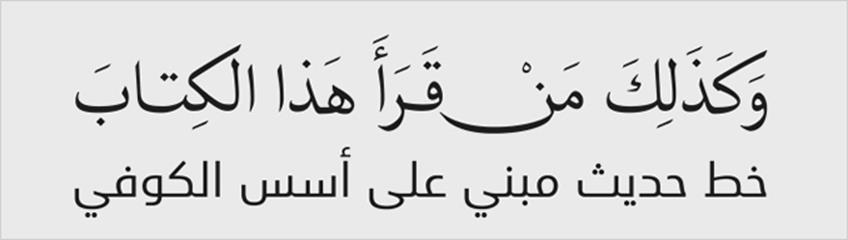
서로 다른 캘리그라피 스타일 예시
Afandem: 전형적인 Naskh 캘리그라피에서 영향을 받은 역동적인 서체
Universe Next Arabic: Kufi 구조에 기반을 둔 현대적인 아랍어 서체 디자인을 구현했다.
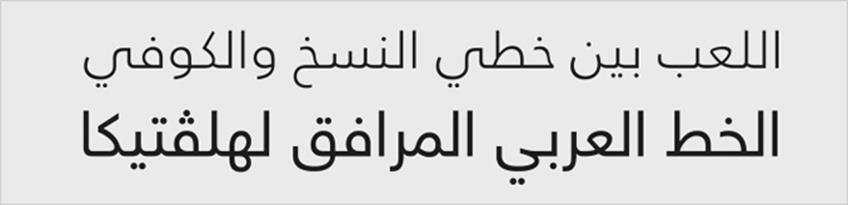
혼합형 디자인 예시. Frutiger Arabic과 Neue Helvetica Arabic
이렇게 작업하는 동안에도, 가장 중요하게 생각하는 부분은 원래의 캘리그라피 형태로 돌아가서 그 형태가 완성된 방식을 이해하고, 그 특징을 최상으로 해석해내는 방법을 찾는 것입니다.
CD:
아랍어와 라틴 문자의 동반 서체 관계는 명백하게 당신이 디자인한 많은 서체들의 핵심이라고 할 수 있습니다. 서로 다른 문자를 동시에 다루며 디자인할 때 고려하는 전략에 대해 조금 더 설명해주실 수 있을까요?
NC:
서로 다른 문자를 함께 디자인할 때 첫 번째 고려하는 사항은 각 문자가 본래 가지고 있는 고유의 시각적 미와 구조를 최대한 살리는 것입니다. 이 부분은 넘어서지 말아야 할 한계선 같은 것이죠. 그 다음 고려사항은 어떻게 두 활자체가 서로 연관되어 있는가 하는 것입니다. 그 둘이 같은 속도로 걷고 있는지, 둘이 같은 톤의 목소리를 내고 있는지, 둘이 같은 방식으로 작동하고 있는지, 그리고 그 둘이 정말로 한 가족의 일부인지. 이러한 사항들을 다루는 건 라틴 문자와 아랍어를 동시에 작업할 때 더 수월합니다. 이것이 바로 Koufiya가 서로 어울리는 동반 서체가 된 방법입니다.
저는 라틴 문자와 아랍어를 교차하며 변화를 만들어냈고, 두 문자가 한쪽에 맞춰 변형되지 않으면서 둘이 함께 목소리를 잘 내는 것처럼 보이도록 노력했습니다. 동반 서체를 디자인할 때는 각 문자가 서로 다른 에너지(dynamics)를 갖고 있다는 사실을 받아들여야 해요. 그리고 이러한 각 문자의 고유성은 반드시 존중되어 디자인에서 잘 설명되어야 합니다. 이중언어로 디자인할 때 보통 아랍어가 라틴 문자에 비해 약해 보이거나 덜 정제되어 보이는 경우가 있는데, 저는 이 상황이 달갑지 않아요. 그래서 저는 Koufiya를 디자인할 때 두 문자가 동등한 시각적 상태를 가질 수 있도록 애썼죠.
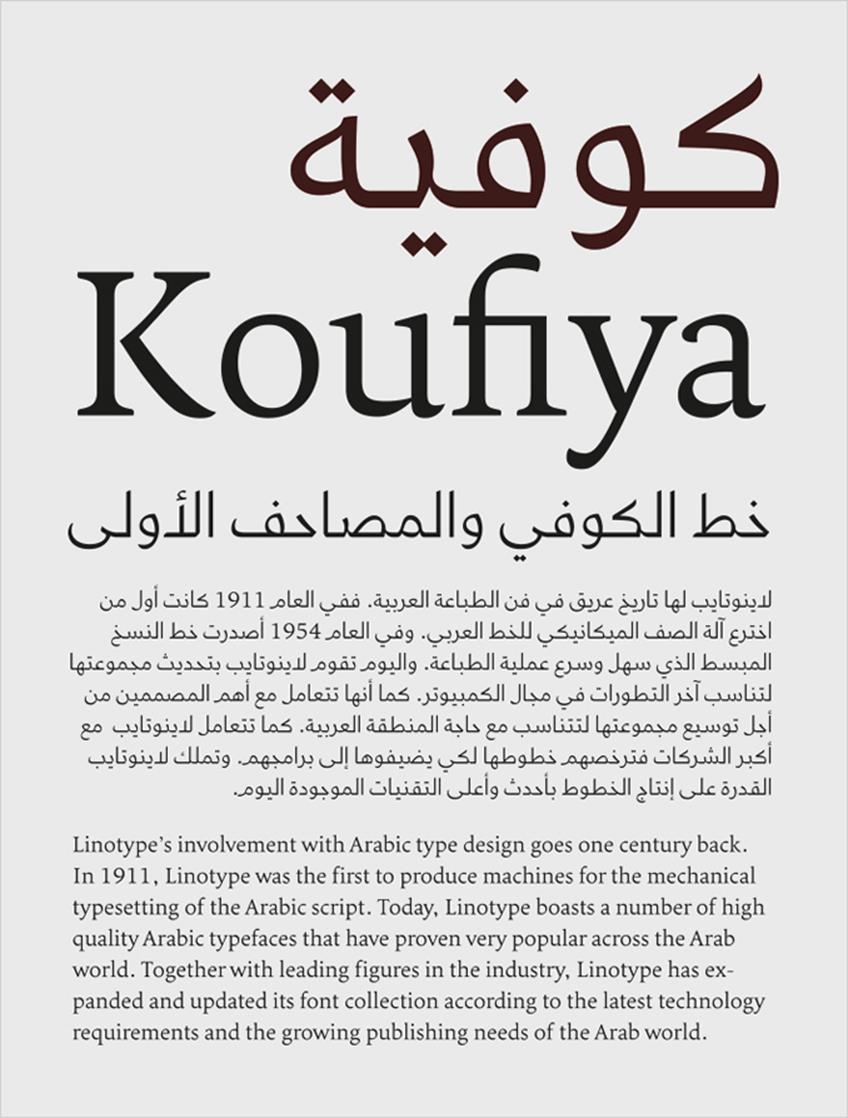
서로 다른 캘리그라피 스타일의 예시.
Universe Next Arabic: Kufi 구조에 기반을 둔 현대적인 아랍어 서체 디자인
저의 그 다음 프로젝트였던 ‘Frutiger Arabic’에서는, 라틴 문자의 디자인이 이미 상당히 잘 짜여 있었습니다. 글자 크기, 웨이트, 대비, 선 처리, 최종마무리, 전반적인 디자인의 표현 그리고 분위기까지 이미 거의 결정되어 있었죠. 이미 잘 결정된 디자인 내용들을 효과적으로 다뤄서 아랍어에 최적으로 적용하는 일만 남아있었어요. Frutiger Arabic과 제 모든 산세리프 동반 서체 디자인에는 딜레마가 있었는데, 그건 본문지향적인 Naskh 모델과 덜 본문 지향적인 Kufi 모델 두 가지 사이에서의 선택과 구조에 대한 의문이었습니다. 이에 대한 제 해결책은 Kufi에 근거한 구조에 Naskh의 필기체적인 특성을 가미한 혼합 접근법이었습니다. 이 접근 덕분에 서체가 헤드라인과 짧은 본문 양쪽에서 동시에 잘 작동하는 것이 가능했죠. 누군가는 Frutiger가 짧은 본문보다 더 긴 본문에도 사용할 수 있다고 말할 수 있습니다. 그 부분에서 저는 애초에 Frutiger가 공항의 사인 시스템(sign system)에 사용하기 위해 만들어졌다는 사실을 상기해야 했습니다.
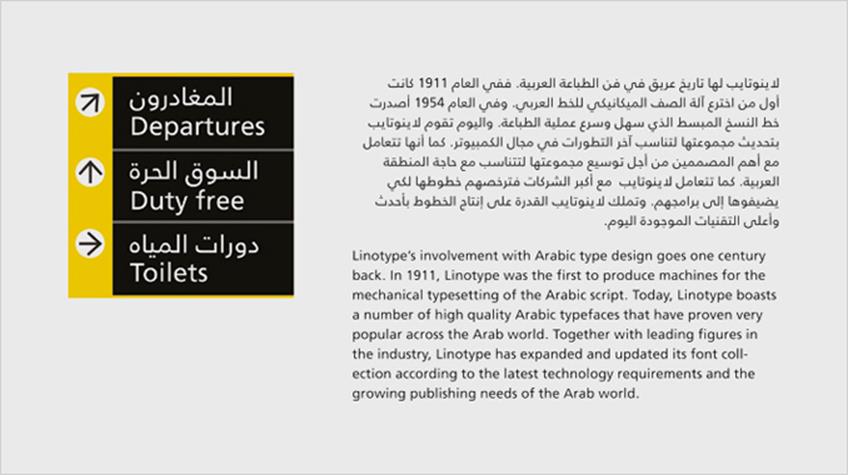
Frutiger Arabic
서로 다른 문자를 함께 디자인할 때 저는 근본적인 질문을 합니다. “시각적 스타일이 매치되도록 디자인해야 할까, 아니면 의도된 기능에 적합하도록 디자인해야 할까?” 다행히 Frutiger Arabic을 작업할 때 저는 한쪽을 선택할 필요가 없었습니다. 이 서체가 시각적으로도 기능적으로도 모두 어울렸기 때문이죠. 하지만 Palatino Arabic 프로젝트에서 위 질문에 대한 결정이 중요했어요. 그때 저는 기능적인 측면에 맞추기로 결정했었죠. 아랍어 동반 서체는 본문 서체로 잘 기능하는 것이 중요합니다. 그래서 두 동반 서체를 자세히 살펴보면, 리듬의 세부나 선 처리, 전반적인 텍스처가 다르다는 점을 알 수 있어요. 그러나 두 서체는 유사한 시각적 사이즈와 웨이트, 대비감, 헤만 사프(Hermann Zapf)의 터치를 공유하고 있죠.
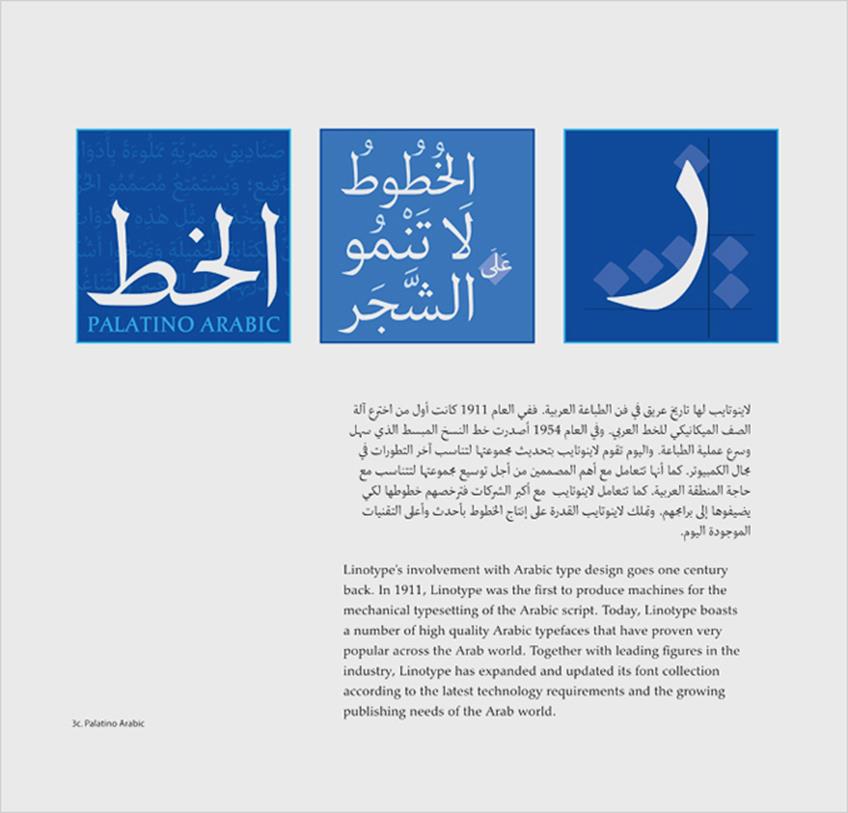
아랍어 서체 조판의 가독성에 대한 나딘 차하인 박사과정 연구로 개발한 역동적인 서체 시스템
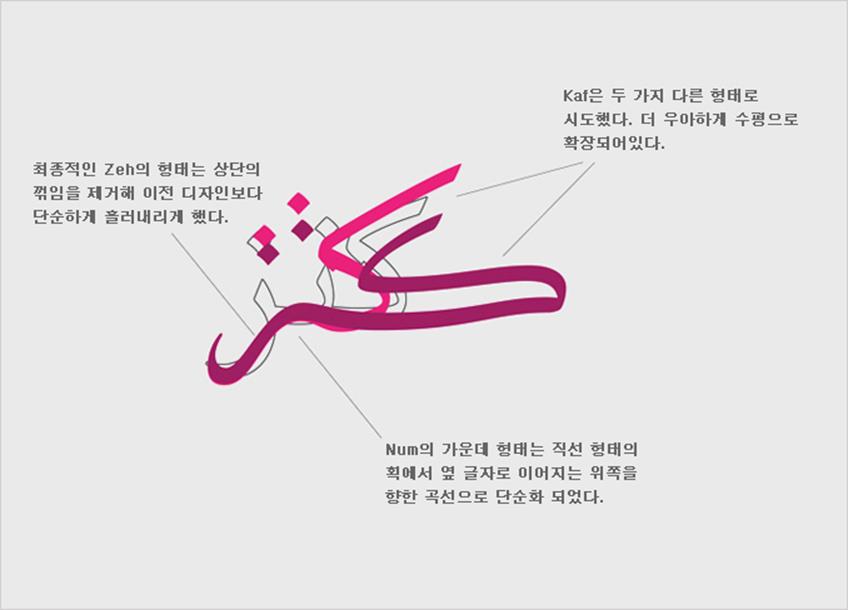
위 이미지는 같은 단어의 글자가 다른 방식으로 조합되는 방식을 보여준다. 아웃라인 형태는 Simplified Arabic 서체로 라틴 문자와 같은 순열 서체이지만 오른쪽에서 왼쪽 방향으로 놓이는 것이 다르다. 이 글자의 형태는 앞이나 뒤에 조합되는 글자에 따른 변화가 없다.
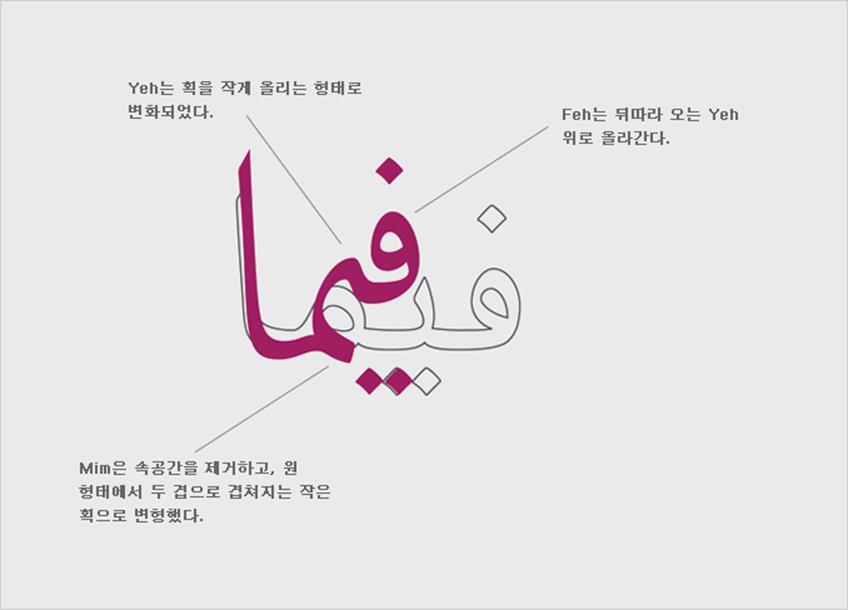
보라색 형태는 새로운 Dynamic Arabic 서체이다. 이 시도는 손으로 그린 아랍어 캘리그라피의 몇 가지 특징을 응용한 것이다. 이 글자의 형태는 앞뒤에 조합되는 글자의 영향을 받는다. 디자인이 더 우아해졌음에도 불구하고, 최종적인 결과는 더 복잡해졌다.